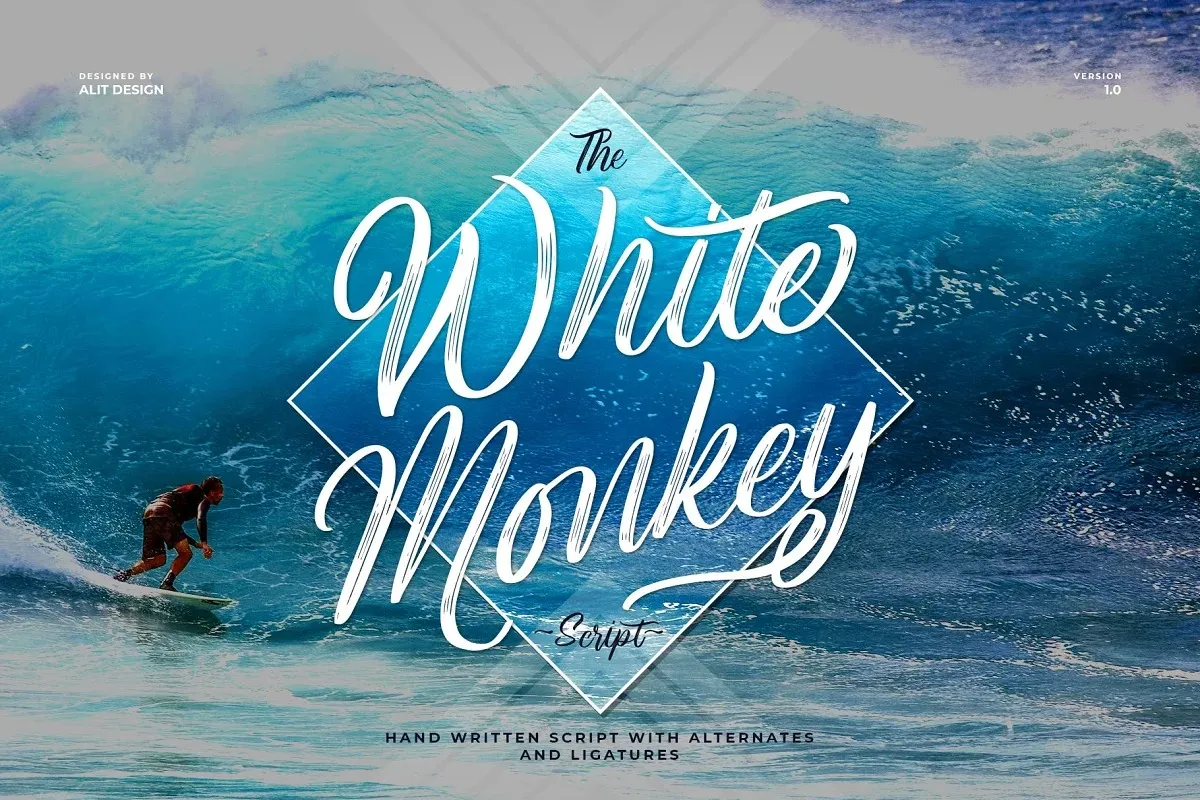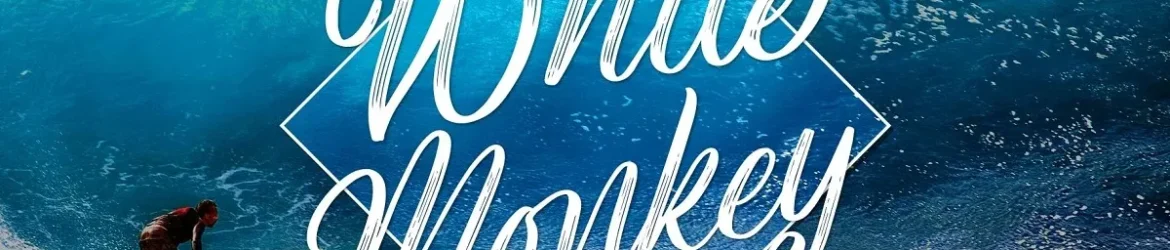
White Monkey Font – Download Grátis
A nova ‘White Monkey Font’ é uma trilha script superaquecida, com um estilo vibrante para desenhos urbanos que se movem pelo papel, prontos para encher a página de energia. Este font foi projetado e compartilhado por alit design, e vem fornecendo designers com um verdadeiro segredo em forma de ligação entre os caracteres da fonte. Possui uma ligação única, trazendo uma surpresa visualmente linda para cada caractere. É perfeito para qualquer necessidade de design que exigir um toque único de personalização: citações impressas, cartões de convite, redes sociais, embalagens de produtos, sites e muito mais. Seja você um profissional ou um designer aficionado, ‘White Monkey Font’ é certamente um upgrade para suas próximas criações digitais.